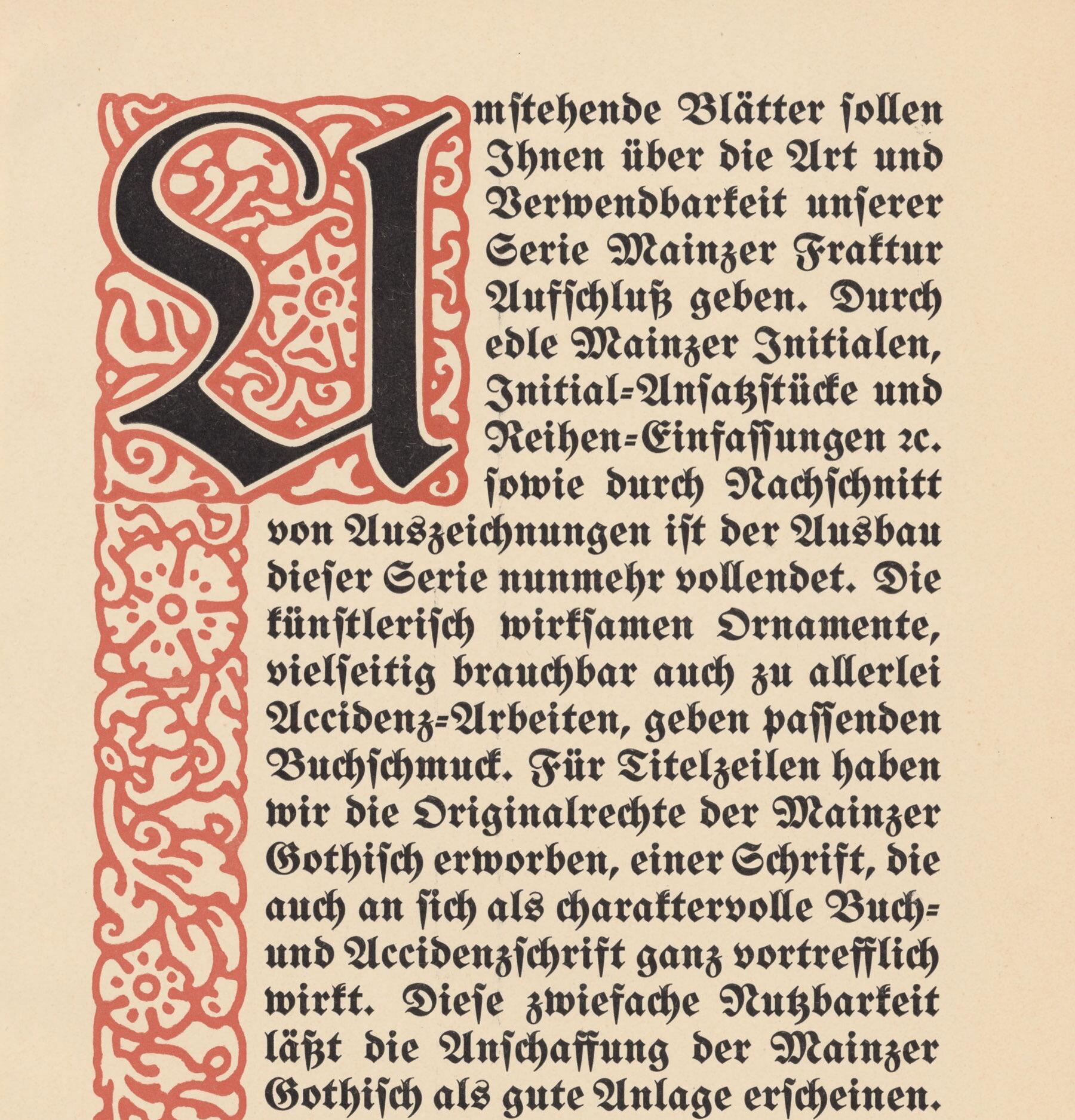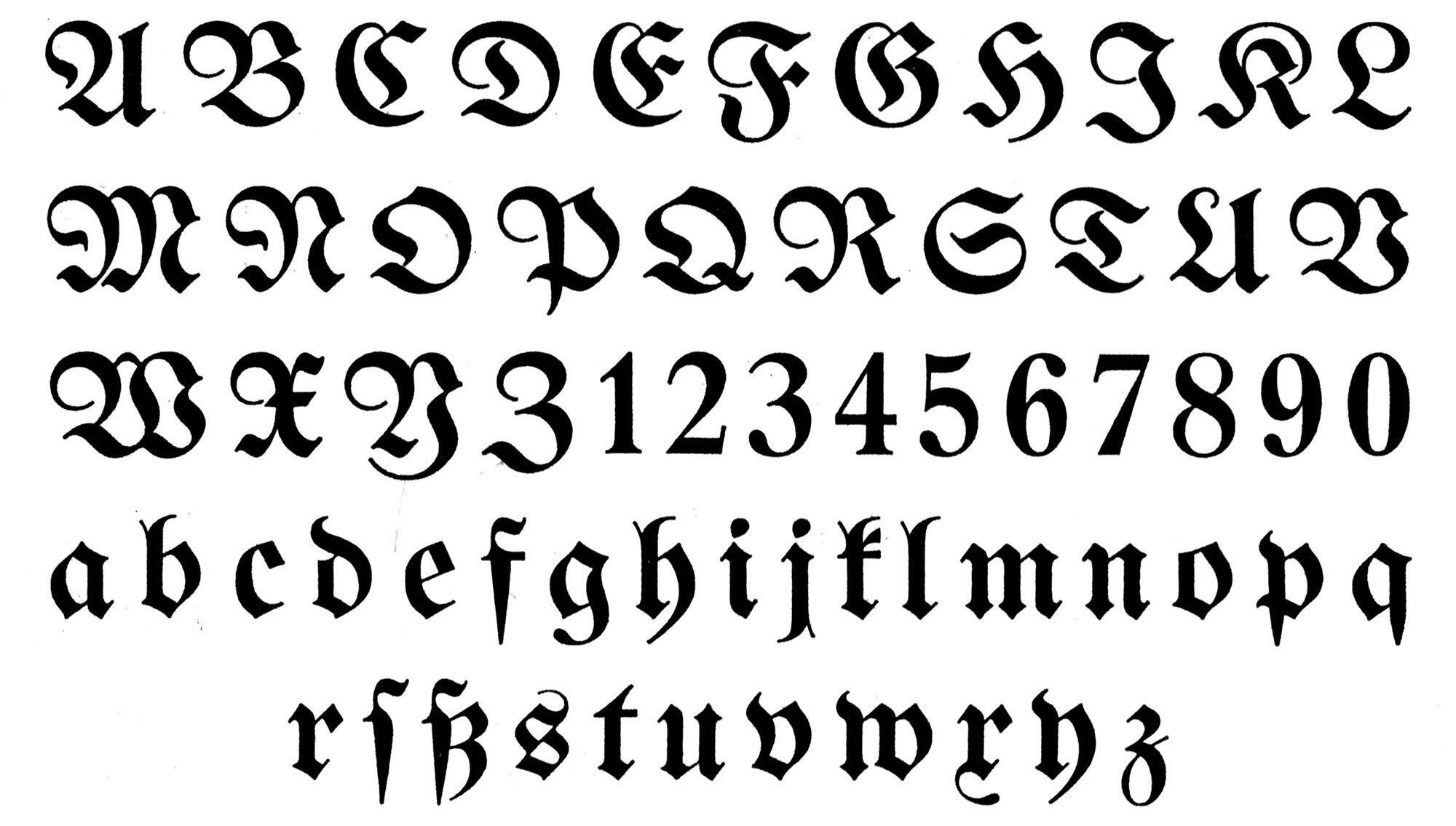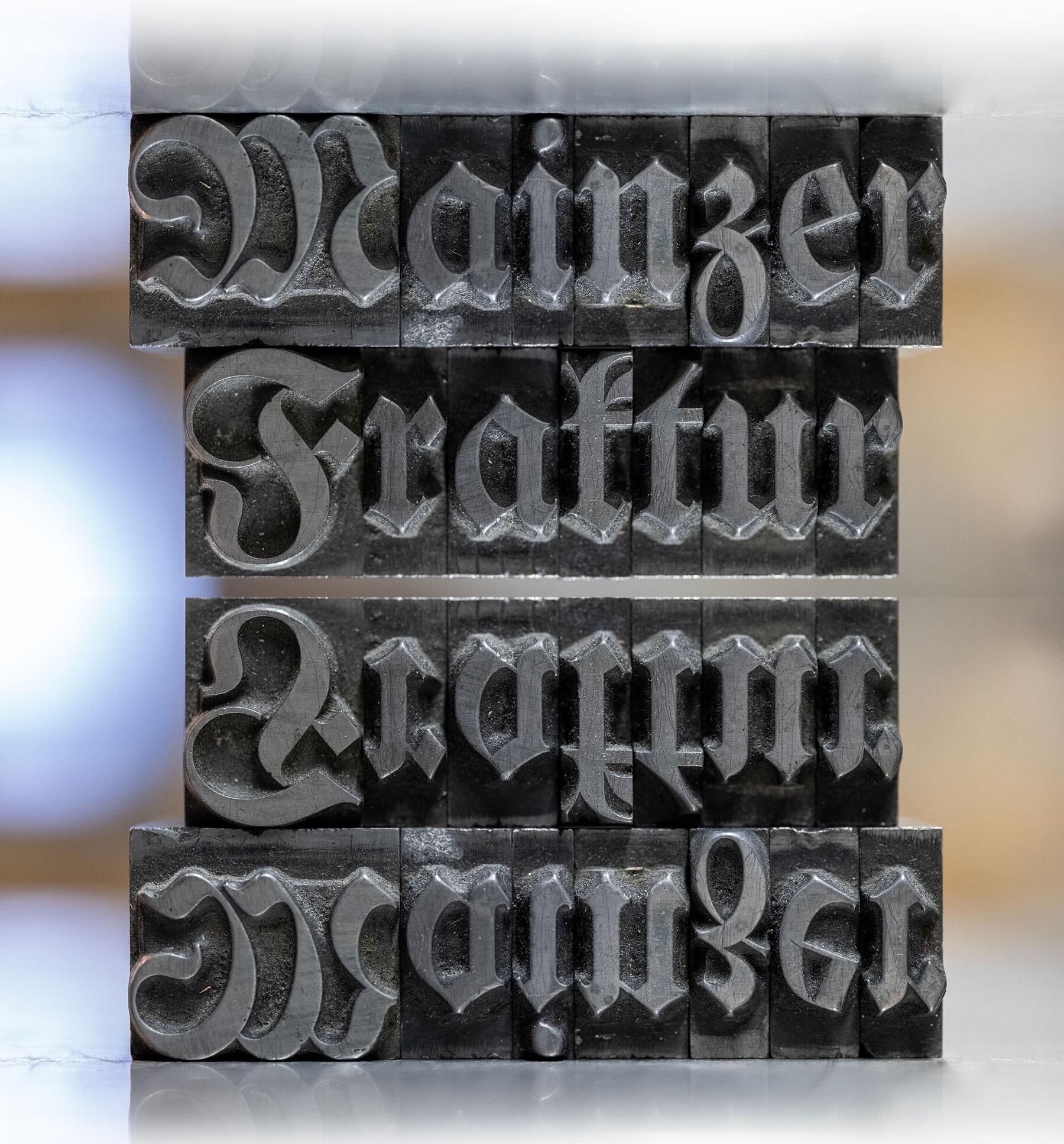
Die Mainzer Fraktur wurde Ende des 19. Jahrhunderts bei der Schriftgießerei Bauer & Co. in Stuttgart entwickelt. Nach der Übernahme der Gießerei durch die H. Berthold AG erschien die Schrift dort 1901. Zudem erschienen fette Versionen, Einfassungen, Ornamente und Initialen.
Muster der Bleisatzversion
Bleisatzmuster mit Schmuck